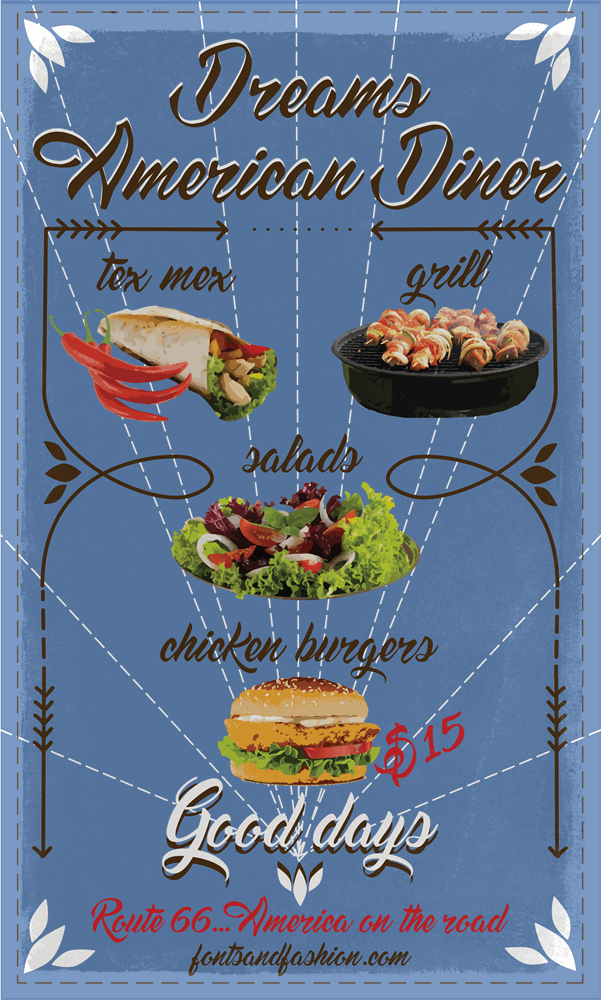
Esta font ‘Dream American Diner’ é uma composição única para escrita filigranada, desenhada pelo talentoso Hamilton. Seu estilo retrata os detalhes de uma antiga cafeteria americana nostálgica, com traços suaves e personalizados que remetem aos ambientes charmosos dos anos 50. A font é ideal para quem deseja dar um toque especial a seu design ou marca, imprimindo um ar retro e autêntico sem perder a elegância contemporânea. Composto por uma gama de caracteres, desde as minúsculas mais delicadas até o maiúsculo, esta font oferece a possibilidade de criar textos atraentes e memoráveis. Para aqueles que desejam explorar ainda mais os recursos dessa fonte, Hamilton disponibilizou links para outros sites online onde você pode encontrá-la. Além disso, se quiser seguir sua evolução ou até mesmo manter-se atualizado sobre novas fontes, é recomendável acompanhar suas redes sociais. O projeto ‘Fonts and Fashion’ e seu designer Hamilton não só oferecem uma ampla gama de recursos gráficos, mas também estabelecem um elo com seus seguidores por meio das mídias sociais. Essa integração faz parte do apelo da font, criando uma conexão emocional entre os usuários e o produto.